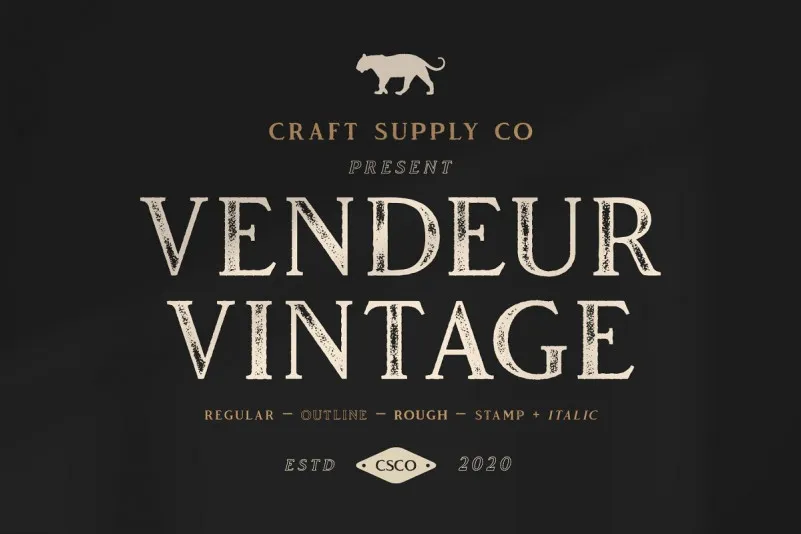
A fonte Vendeur Vintage é uma elegante combinação do estilo retro clássico dos anos 80 com elementos modernos e vibrantes. Ela é perfeita para aqueles apaixonados por design vintage, oferecendo um toque de sofisticação e charme na hora de trabalhar em projetos gráficos. Esta fonte foi criada com uma sensibilidade artística que permite incorporar tanto elementos tradicionais quanto a modernidade contemporânea, resultando num resultado visual vibrante e inovador. A Vendeur Vintage é perfeita para criações de design impresso ou digital, permitindo-lhe explorar o seu imaginário através da adição de pequenas definições em Extras – tornando seus projetos ainda mais vivos e impecáveis. Como uma fonte vintage moderna, a Vendeur Vintage está equipada para moldar qualquer projeto ao seu estilo próprio, tornando-o único e incrivelmente original.